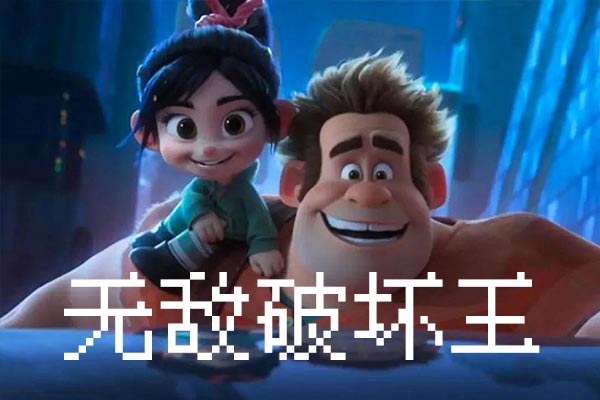
凤凰点阵体(VonwaonBitmap)是由中国大陆的Haoyu Qiu创作的免费中文像素字体,使用CC0 1.0协议公开发布。其字模基于开源项目BitmapFont优化,适合汉字和非汉字、不同字号和字体间的搭配。
在图形化操作系统普及后,矢量/向量字体因其平滑渲染和无限放大功能成为主流。相比之下,点阵字体在显示效果上稍显不足。
凤凰点阵体包含两个版本:12px和16px,对应9pt和12pt的基准字模像素高度。当字号设置为对应尺寸的整数倍时,TTF字体的显示效果最佳。
凤凰点阵体共包含7543个字符,其中汉字6763个。对于注重文件大小的用户,可以选择Lite版,它包含4041个字符,其中汉字3755个,但不包括日文假名、希腊字母、俄文字母、拼音、注音符号、制表字符和序号字符。